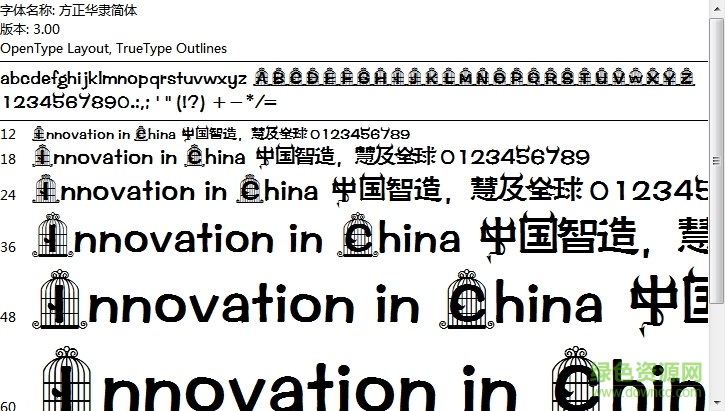
惡魔小尾巴字體ttf
惡魔小尾巴字體是一款在方正華隸簡體上美化修飾而來的藝術(shù)字體,增加了小尾巴團(tuán),更有類似鳥籠的設(shè)計(jì),讓文字活潑省去,更具創(chuàng)意,如果你喜歡,就來綠色資源網(wǎng)體驗(yàn)吧!
惡魔小尾巴字體ttf特色
惡魔小尾巴字體是一款用于非主流設(shè)計(jì)方面的字體,整體風(fēng)格非常的出眾,線條粗細(xì)適中,帶有惡魔小尾巴的圖案,十分有趣!
惡魔小尾巴的字體
惡魔小尾巴中文字體與方正華隸簡體比較相似,增加了個(gè)性十足的圖形,給文字更傳神的表達(dá),讓文字內(nèi)容更加靈活起來,適合于萬圣節(jié)氣氛、兒童趣味內(nèi)容的內(nèi)容設(shè)計(jì)。